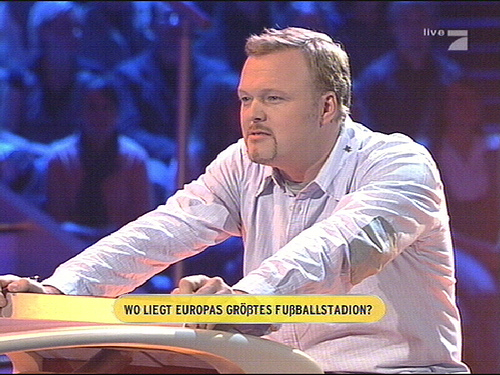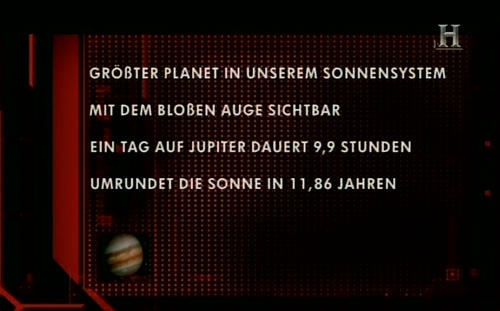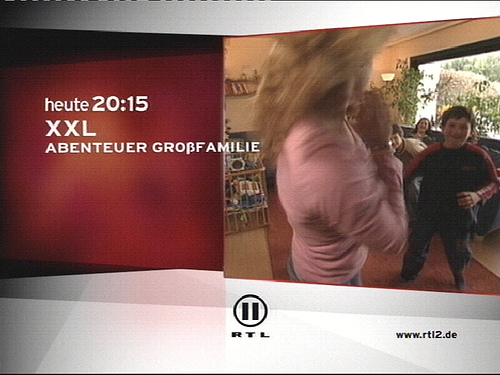
Ich verstehe nicht, wie die Gestalter bei so einem großen und reichen Sender wie RTL es nicht auf die Reihe bekommen, ganz einfache microtypografische Regeln einzuhalten :?
Ich bin bestimmt nicht der Einzige hier im Forum dem die Zollzeichen ("abc") anstelle der korrekten Anführungszeichen („abc“ oder »abc«) bei Wer Wird Millionär aufgefallen sind, oder? Und auch bei SternTV sieht man immer wieder die Zollzeichen. (Und andere typografische Unkorrektheiten wie z.B. Leerzeichen vor Satzzeichen.)
Ich sehe es ja ein, dass man hier im Forum (auch wenn es ein bzw. DAS Typoforum ist) aus Bequemlichkeit mal die Zollzeichen nimmt (geht ja auch schneller) ... aber legen denn Fernsehsender wie RTL keinen Wert auf korrekte Typografie? Wer bei RTL in irgendwelchen gestalterischen Bereichen tätig ist, müsste sich doch eigentlich in der Typografie auskennen?!
... is doch für RTL eigentlich eher peinlich! Zollzeichen sind nunmal nicht dafür gedacht ... da könnten die es ja auch gleich so machen: %abc% oder so: cmabccm :mrgreen:
Was sagt denn ihr dazu? Stört euch das denn nicht genauso?
ja, mir ist das erst kürzlich aufgefallen. ich weiss nicht mehr genaus was es war aber es war irgendeine vorschau auf rtl oder pro7 wo falsche anführungen verwendet wurden. das war aber nicht irgendeine unterzeile, sondern ein richtiger titel ... schade ich erinnere mich nicht mehr an die sendung die beworben wird.
was willste da machen, rtl hat ja ihrre eigene werbeabteilung, rtl creations und wenn die keine ahnung haben oder nur den praktikanten ranlassen, dann passiert sowas halt. ist zwar peinlich aber der 08/15 zuschauer wird es eh nicht bemerken.
ich nutze im forum auch immer diese "zeichen" einfach weil es schneller geht, darum lese ich hier auch nicht korrektur und schreibe alles klein. ich will nicht er groß überlegen, die postings passieren ja teilweise neben der regulären arbeit. ansonsten setzte ich aber zu 98 % immer die französischen »anführungen« da sieht man aber auch oft falsche anwendungen «so zum beispiel» – und damit meine ich nicht unsere schweizer freunde. :nana:
... aber der 08/15 zuschauer wird es eh nicht bemerken.
Das stimmt zwar, ist aber noch lange kein Grund für das RTL Creations-Team, es nicht richtig zu machen!
Schämen sollte man ohne "h" schreiben…
WWM kommt aus den USA und wird weltweit mit den amerikanischen Anführungszeichen gesetzt. Nachdem das Zollzeichen nirgends definiert ist kann es sich dabei genausogut um Anführungszeichen handeln …
:oops: ... oh, du hast Recht, das h müsste weg! :oops:
WWM kommt aus den USA …
Und was ist mit SternTV? Kommt das auch aus den USA?
Wenn bei WWM die Fragen auf deutsch gestellt werden, sollten sie doch eigentlich nicht nur der deutschen Rechtschreibung, sondern auch der deutschen Typografie gerecht werden? Ich kann mir nicht vorstellen, dass das mit den Zollzeichen Absicht ist!
Die paar TV-Fuzzis, die ich so kenne, würden das auch nicht richtig machen. In diesem RGB-Modus arbeiten Grafiker, keine Setzer. Die wissen das einfach nicht - und halten sowas auch nicht für wichtig.
Glaube ich auch. Ist auch kein RTL-spezifisches Problem, sondern gilt für alle Sender.
Mit Eszetts stehen sie übrigens auch auf dem Kriegsfuß:
ich finds ja immer lustig wenn bei MTV in dieser schriftbanner neben dem logo keine sonderzeichen angezeigt werden, da fehlen dann auch gerne mal die umlaute oder es kommen irgendwelche kryptischen zeichen. schreibfehler kann man dort auch oft entdecken.
Ja, da hab ich auch schon oft gelacht, wenn die da irgendwelche Freefonts runterladen ohne zu merken, dass die Umlaute nicht angezeigt werden. Aber das versendet sich ja, so lautet die Standardausrede ...
Nebenbei: Wie hier schon besprochen, ist ? (U+2033) das Zollzeichen, " (U+0022) dagegen das ASCII- und Schreibmaschinen-Anführungszeichen. Völlig falsch ist es damit meiner Meinung nach eigentlich gar nicht, unschön natürlich trotzdem.
Da gehen die Meinungen aber weiterhin auseinander, eine Definition gibt es nicht.
Ja, da hab ich auch schon oft gelacht, wenn die da irgendwelche Freefonts runterladen ohne zu merken, dass die Umlaute nicht angezeigt werden. Aber das versendet sich ja, so lautet die Standardausrede ...
nein, ich denke nicht das es irgendwelche freefonts sind, den die schriften und viva und mtv sind ja meistens alles corporate fonts, jedenfalls die aktuelle von mtv, die hat gleich diesen balken im font mit dran. ich denke eher das es ein internes problem mit der software ist, oder einfach die unwissenheit wie man das system richtig füttert damit auch richtige ergebnisse rauskommen.
Stimmt! Ich hab vor einer ganzen Weile wirklich mal versucht, die WWM-Redaktion darauf hinzuweisen ... die haben mir auch ne Mail geschrieben, dass sie es weitergeleitet haben ... danach habe ich nichts mehr von denen gehört und es hat sich auch nichts getan.
Die haben das vermutlich nicht ernst genommen!? :? (Das wundert mich aber nicht.)